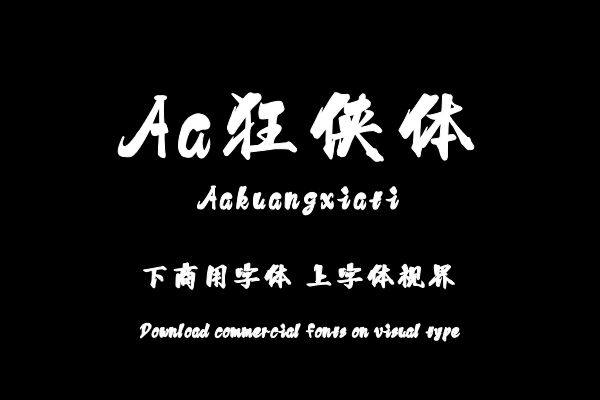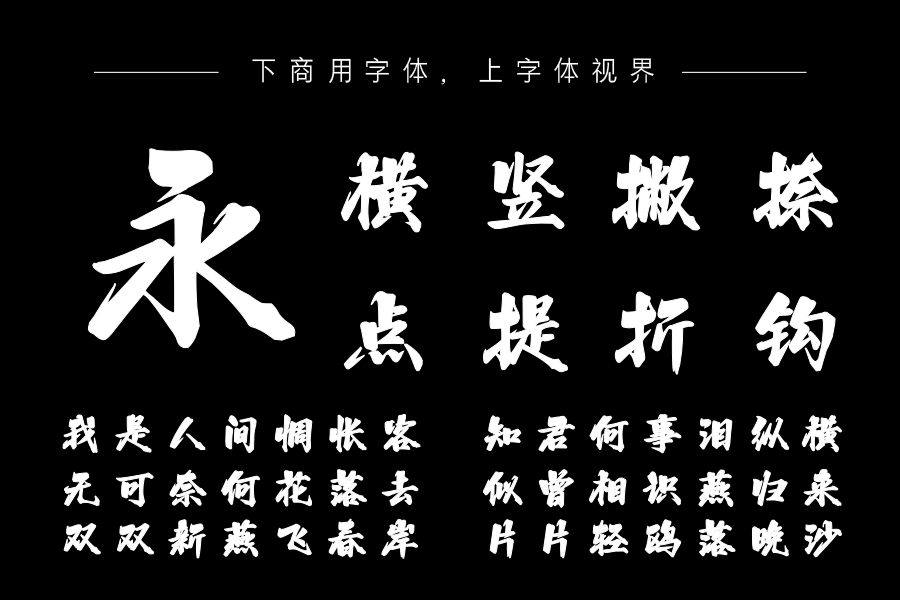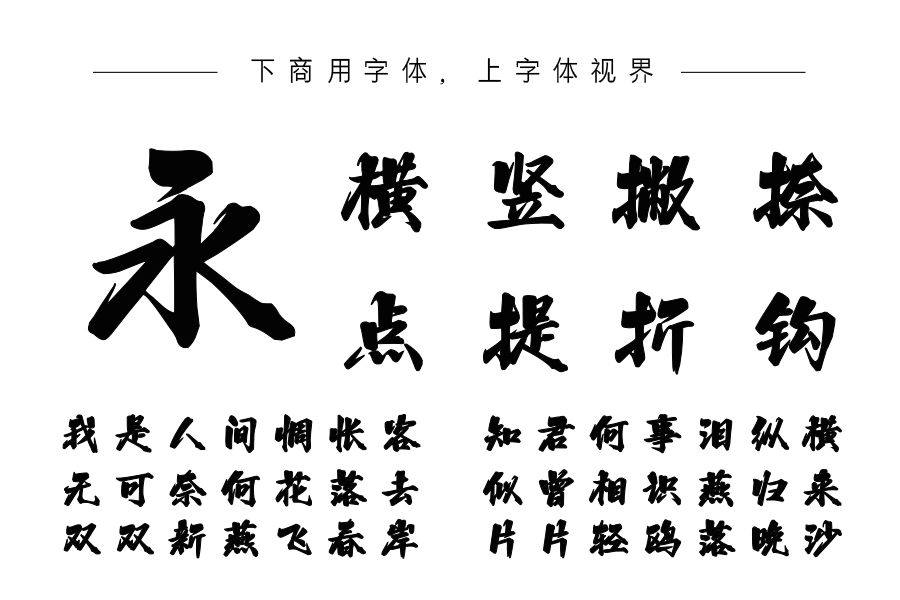
这款字体具备传统行楷的笔画写法的同时,以外部虚笔画向四角放射来强调内收外放,相对上部空间更大外放更加明显,中宫偏低,形成不同于传统行书的强烈张力,更适合表现豪迈......购买须知:“下载服务费”与“字体VIP”所获得字体 仅用于个人非商用, 商用请联系付费授权。本字体为电脑用字,手机没有root权限不支持直接手机换字(手机如何root,请自行百度搜索教程)。购买前请先 了解清楚后再付款 ,字体为虚拟产品无法回收 一旦购买不支持退款。